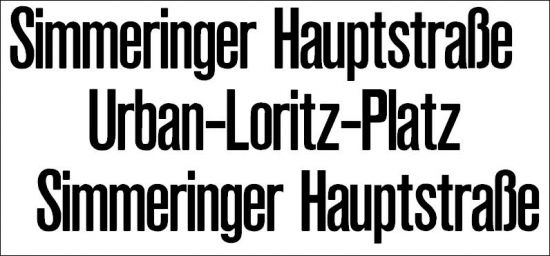
Schriftart Wiener Linien - alte Zielschildtafeln
Welche Schriftart wird auf diesen Tafeln verwendet?
Bzw. welche Schriftart sieht dieser zum Verwechseln ähnlich?
Kennzeichen:
- sehr spezifisch aussehende "b", "S" und "s"
- kaum Variation der Schriftdicke
- serifenlos (kaum übersehbar :wink: )
- "geschlossene" 4
- Größenverhältnis Groß- zu Kleinbuchstaben: 1:0,8; Unterlänge 0,2
- Buchstabenbreite entspricht dreifacher Linienbreite